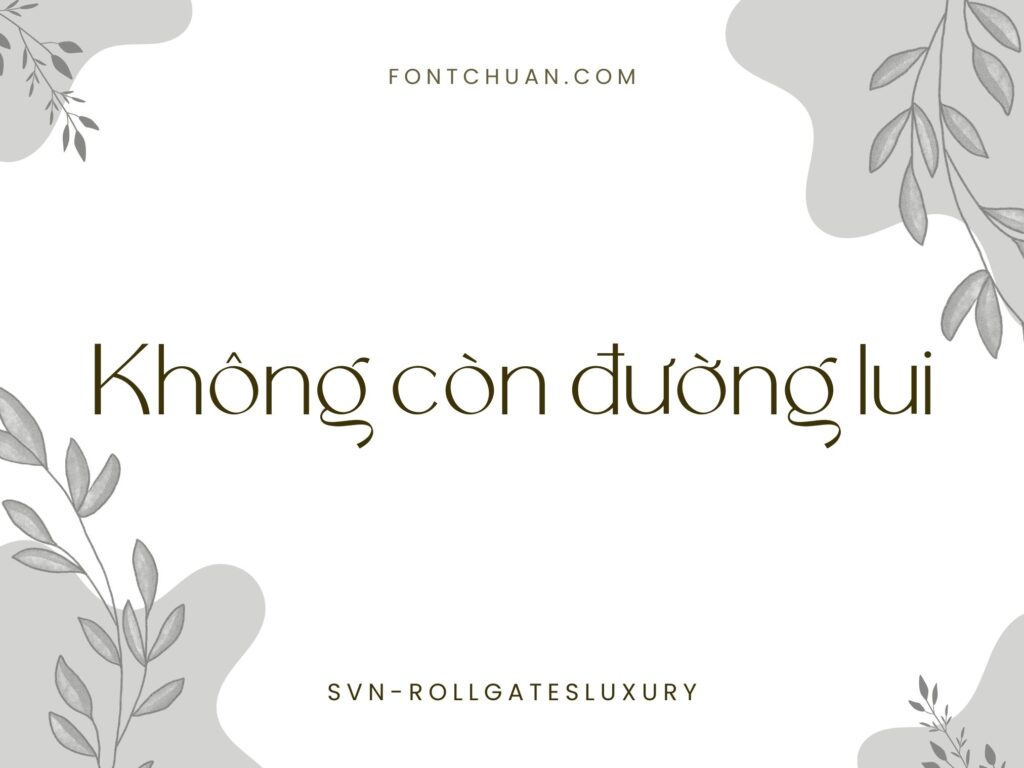
Font SVN Rollgates Luxury Việt Hóa
Font SVN Rollgates Luxury là phiên bản Việt hóa của kiểu chữ Rollgates Luxury, được thực hiện bởi STYLEno.1 Fonts. Đây là một font sans-serif kết hợp giữa sự thanh lịch cổ điển và hiện đại, được thiết kế bởi Cotbada Studio. Font này lý tưởng cho việc tạo thiệp mời đám cưới, sử dụng trong bố cục tạp chí hoặc bất kỳ thiết kế đồ họa nào yêu cầu vẻ ngoài tinh tế với phong cách vintage. Rollgates Luxury bao gồm các ký tự chữ hoa, chữ thường, chữ số và dấu câu, hỗ trợ đa ngôn ngữ. ([STYLEno.1 Fonts](https://www.svnfont.com/viet-hoa-svn-rollgates-luxury/))
SVN Rollgates Luxury phù hợp cho các dự án thiết kế yêu cầu sự sang trọng và chuyên nghiệp, như thiết kế logo, tiêu đề, bao bì sản phẩm và các ấn phẩm truyền thông. Các ngành nghề như quảng cáo, bất động sản và giáo dục có thể tận dụng font này để tạo điểm nhấn trong thiết kế. Ngoài ra, font cũng thích hợp cho các sự kiện như Tết, Giáng sinh, Valentine và các lễ hội khác.